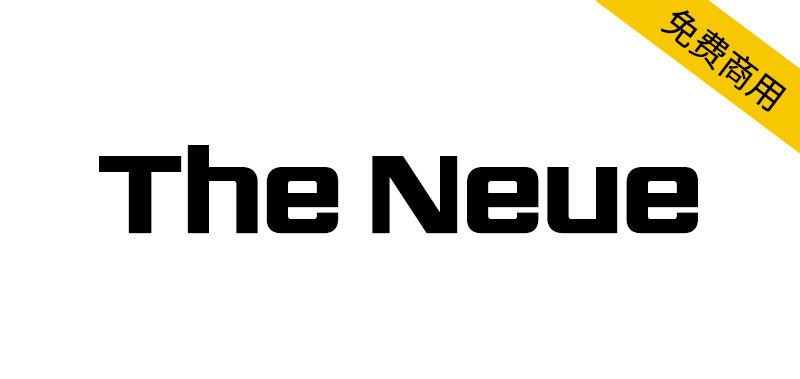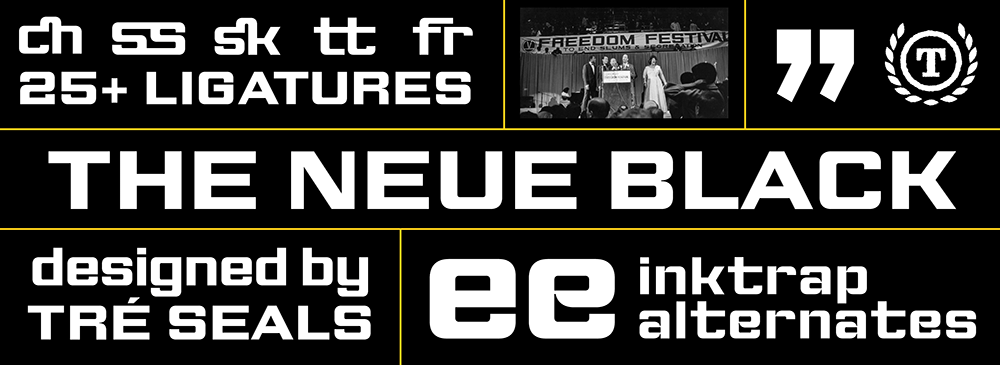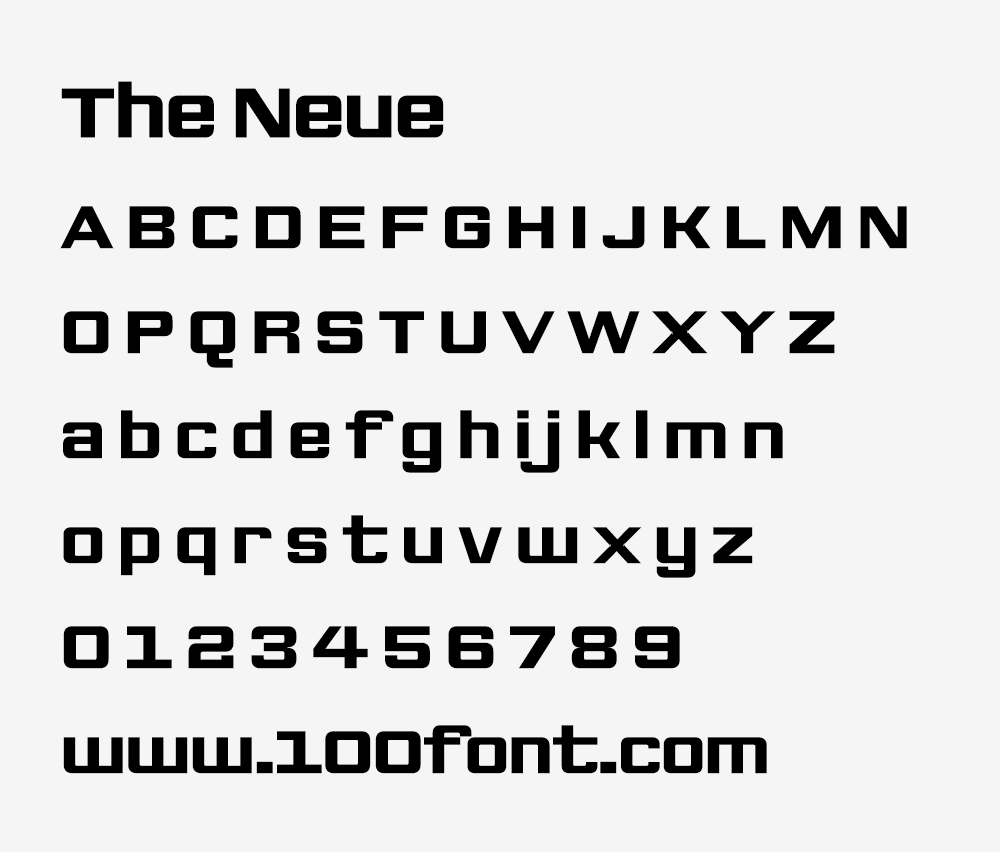
The Neue是与Vocal Type Co.的设计师特雷·西尔斯(Tré Seals)合作完成的。这款无衬线字体拥有强大的字符集,包含25种以上连字及多种油墨陷阱替代字形。
该字体创作于2020年,其设计灵感源自芝加哥自由运动的街头标识。这场由马丁·路德·金博士和南方基督教领袖会议(SCLC)发起的民权倡导运动,标志着他们的平权活动从美国南部扩展至北方城市。运动核心旨在针对非裔社区存在的住房种族歧视与企业雇佣歧视问题。
1966年7月芝加哥西区爆发种族骚乱后,该运动通过示威游行持续扩大影响力。在8月5日一次全白人社区的游行中,黑人示威者遭遇严重敌意——砖块与玻璃瓶横飞,金博士本人也被石块击中。事后他坦言:"我在南方参与过无数示威,但从未遭遇像今天这般充满仇恨的敌意。"
八月底,芝加哥市长戴利急于平息示威。经与金博士及多个住房委员会谈判后,各方达成协议:芝加哥住房管理局承诺建造不限高度的公共住房,抵押银行家协会同意取消种族限制的贷款政策。峰会协议签署后,部分SCLC成员留守芝加哥协助住房计划与选民登记,金博士本人也驻留至1967年1月。虽然市政官员未切实履行住房改革承诺,但这场运动仍取得了部分阶段性成果。
The open-source release of The Neue Black is in partnership with designer Tré Seals of Vocal Type Co. The Neue Black is a display sans serif with a robust character set that has over 25 ligatures and various inktrap alternates.
Created in 2020, The Neue Black is based on the signage from the Chicago Freedom Movement, an advocacy campaign spearheaded by Martin Luther King Jr. and the Southern Christian Leadership Conference (SCLC). The campaign marked the expansion of their civil rights activities from the South to the northern cities. At the center of their campaign, they targeted racial discrimination in housing and racist hiring practices by companies in African American neighborhoods.
The campaign had gained momentum through demonstrations and marches when race riots erupted on Chicago’s West Side in July 1966. During a march through an all-white neighborhood on August 5th, Black demonstrators were met with hostility. Bottles and bricks were thrown at them, and King was struck by a rock. Afterward, he noted: I have seen many demonstrations in the South but I have never seen anything so hostile and so hateful as I’ve seen here today.
By late August, Chicago’s Mayor Daley was eager to find a way to end the demonstrations. After negotiating with King and various housing boards, an agreement was announced in which the Chicago Housing Authority promised to build public housing with limited height requirements, and the Mortgage Bankers Association agreed to make mortgages available regardless of race. Following the summit agreement, some SCLC staff stayed in Chicago to assist in housing programs and voter registration. King himself stayed in Chicago until January 1967. The campaign’s goals were met with some success, though city officials failed to take concrete steps to address issues of housing despite the summit agreement.